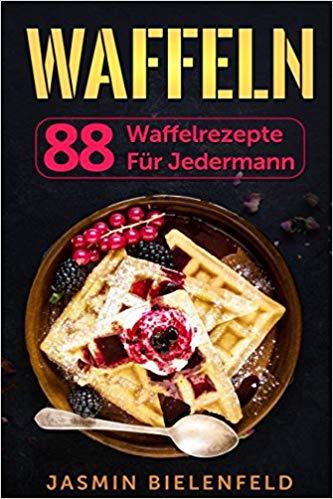
Da scheint es herzukommen – ich hatte es von einem Freund ohne Quellenangabe geschickt bekommen.
Die Schablonenschrift in Kombination mit der 88 ist schon irgendwie schräg. Ich lese zudem immer »88 Waffenrezepte«. :shock:
Braucht man dann einen Waffelnbesitzkarte?
Der langt für Zuhause. Aber in der Öffentlichkeit brauchst Du einen Waffelschein. Und bitte immer das Waffelkontrollgesetz beachten! Leider ist da unser Standörtchen D sehr restriktiv. Nix mit: Freie Waffeln für freie Bürger. :cry:
»Woody, der Unglücksrabe« (1969): Woody will eine Bank ausrauben und schiebt dem Kassierer einen Zettel zu. Der liest: »Benutzen Sie sich unauffällig. Ich richte eine Waffel auf Sie.« - Woody: »Das soll heißen Ich richte eine Waffe auf Sie!« - Kassierer:»Aber da steht eindeutig Waffel.« - Woody: »Das l ist ein Ausrufezeichen. Es heißt Ich richte eine Waffe! auf Sie
Braucht man dann einen Waffelnbesitzkarte?
Kriegste aber nicht, wenn einen an der Waffel hast ...
Aber ...
Genau 88 Rezepte und die Waffeln so gekreuzt hingelegt ...
Hmmm ...
Und im Rezept steht dann wohl auch, dass man die Waffeln Goldbraun backen soll?, damit die eine Gaumenfreude sind.
Da haben wir wohl ein rechtes Rezeptbuch gefunden...
Au weia – da fehlt ja nur noch: „Frieden schaffeln ohne Waffeln.“  :-|
Ach was! Frieden durch Abschreckung! Waffelgleichheit für Alle! Weg mit dem Kriegswaffelkontrollgesetz! Wir brauchen unbedingt einen Waffeldoppelbeschluss! Ansonsten haut uns der Iwan in die Pfanne … äh … ins Waffeleisen!
Seit der Dienst an der Waffel nicht mehr verpflichtend ist, lässt die Ausrüstung (nicht nur der Gulaschkanone) ja sehr zu wünschen übrig. Es steht zu vermuten, dass unsere Waffeln nicht nur fluguntauglich sind, sondern die ein oder andere auch nur noch als Kanonenfutter taugt. Aber immer noch lieber die Waffel in der Hand als die Torte auf dem Dach. Oder wie das heißt … :party:
Essen!
Was Krupp in Eſſen iſt, ſind wir im Trinken!
Probleme mit dem Frakturführerſchein
Also ich bin für Waffelbrüderschaft! Damit das hier nicht noch ausartet. 😀
PS: Kennt jemand ein Waffelrezept auswendig?
Irgendwo steht glaub noch ein seit Jhrzehnten ungenutztes Waffeleisen rum ...
Der Faden macht Appetit ... 🥐🍴